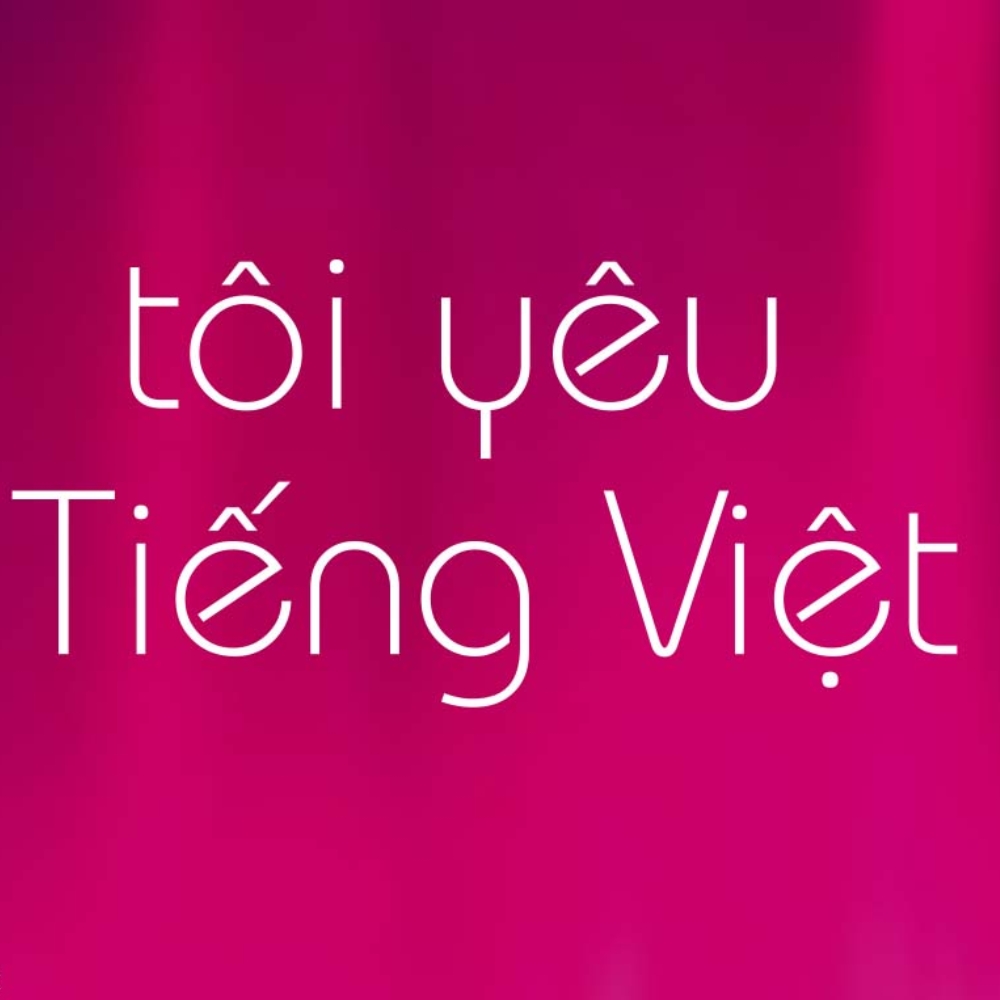
Font Bauhaus việt hóa là font chữ hình học đặc trưng của trường phái thiết kế Bauhaus Đức với phong cách hiện đại, tối giản được sử dụng rộng rãi trong thiết kế bao bì sản phẩm nghệ thuật, túi giấy studio thiết kế và in ấn cho thương hiệu sáng tạo. Font Bauhaus với nét chữ hình học thuần túy, cân đối hoàn hảo tạo cảm giác tiến bộ, đổi mới.
Tên font |
Đặc điểm |
Ứng dụng in ấn tốt nhất |
Bauhaus 93 |
Phiên bản thương mại phổ biến nhất. | Logo nghệ thuật, poster triển lãm. |
Righteous |
Font hình học miễn phí, phong cách Bauhaus. | Tiêu đề lớn, logo sáng tạo. |
Archivo Black |
Font hình học đậm, mạnh mẽ. | Poster, standee, banner sự kiện. |
Sansita |
Font hình học nhiều độ đậm. | Catalogue, brochure linh hoạt. |
Barlow |
Font hình học hiện đại, 18 độ đậm. | Đa năng cho mọi in ấn. |
Lưu ý: Font Bauhaus hình học đẹp cho tiêu đề, logo nhưng khó đọc khi dùng cho văn bản dài. Nên dùng Bauhaus cho các yếu tố nổi bật, còn nội dung chi tiết dùng font không chân thông thường dễ đọc hơn.
Font Bauhaus là gì?
Font Bauhaus được tạo ra dựa trên triết lý thiết kế của trường Bauhaus – trường kiến trúc và nghệ thuật ứng dụng nổi tiếng nhất thế giới, thành lập năm 1919 tại Đức. Bauhaus tin rằng hình thức nên phục vụ chức năng, loại bỏ mọi chi tiết trang trí không cần thiết.
Font Bauhaus do Herbert Bayer thiết kế – sinh viên và sau này là giáo viên tại trường Bauhaus. Bayer tạo ra bộ chữ cái chỉ có chữ thường (không chữ hoa), dựa trên hình tròn, hình vuông và hình tam giác cơ bản.
Đặc điểm của font Bauhaus:
- Hình học thuần túy: Chữ O là hình tròn hoàn hảo, chữ I là đường thẳng, chữ A là hình tam giác – tuân theo quy tắc hình học nghiêm ngặt.
- Nét đồng đều: Độ dày nét chữ đồng nhất, không tương phản giữa nét đậm và mảnh.
- Tối giản: Không chân, không trang trí – chỉ giữ lại điều cần thiết.
- Hiện đại, tiến bộ: Đại diện cho tư duy hướng tương lai của thế kỷ 20.
Triết lý Bauhaus “hình thức tuân theo chức năng” ảnh hưởng sâu rộng đến thiết kế hiện đại. Font này không chỉ là chữ cái mà còn là tuyên ngôn về cách tiếp cận thiết kế – đơn giản, thực dụng, dân chủ (ai cũng dùng được).
Ứng dụng font Bauhaus việt hóa trong thiết kế và in ấn
Font Bauhaus với phong cách hình học thuần túy được ưa chuộng trong nhiều lĩnh vực:
- Biểu tượng nghệ thuật, thiết kế: Bauhaus đại diện cho thời kỳ vàng son của thiết kế hiện đại – sử dụng font này tạo liên hệ ngay với nghệ thuật, sáng tạo, kiến trúc.
- Hiện đại vượt thời gian: Được thiết kế 100 năm trước nhưng vẫn trông hiện đại ngày nay – chứng minh sức mạnh của hình học cơ bản.
- Tối giản mạnh mẽ: Font rất đơn giản nhưng có tính cách riêng – không nhạt nhẽo như font tối giản khác.
- Thể hiện tư duy tiến bộ: Phù hợp thương hiệu muốn truyền tải tinh thần đổi mới, hướng tương lai.
Font Bauhaus xuất hiện trong nhiều sản phẩm in ấn:
- Bao bì sản phẩm nghệ thuật: Bộ màu vẽ, giấy mỹ thuật, dụng cụ thiết kế, vật liệu sáng tạo.
- Túi giấy studio: Công ty kiến trúc, studio thiết kế, phòng tranh nghệ thuật, xưởng thủ công.
- Catalogue triển lãm: Brochure kiến trúc, lookbook thời trang tiên phong, tài liệu nghệ thuật.
- Poster sự kiện: Triển lãm nghệ thuật, hội thảo thiết kế, sự kiện kiến trúc, lễ hội sáng tạo.
- Logo thương hiệu: Startup thiết kế, tạp chí nghệ thuật, thương hiệu thời trang đương đại.
- Bao bì sản phẩm sáng tạo: Đồ handmade cao cấp, sản phẩm thiết kế độc quyền.
3. Tại sao Bauhaus quan trọng trong lịch sử thiết kế?
Trường Bauhaus là trường đầu tiên kết hợp nghệ thuật, thủ công và công nghiệp, tạo ra thiết kế vừa đẹp vừa sản xuất hàng loạt được. Triết lý hình thức tuân theo chức năng, thiết kế cho mọi người, sử dụng hình học cơ bản đã định hình toàn bộ thiết kế hiện đại.